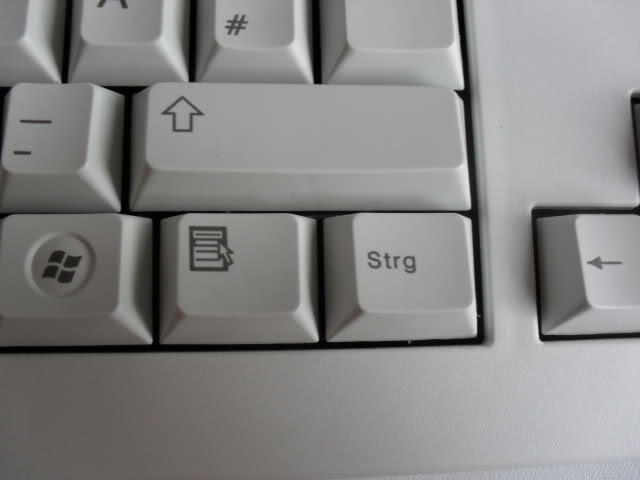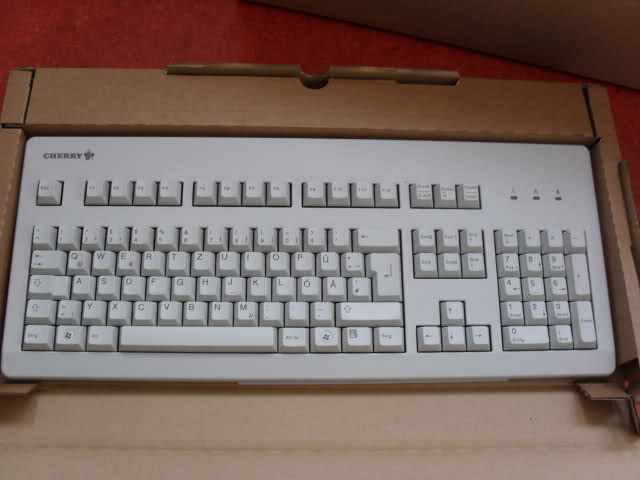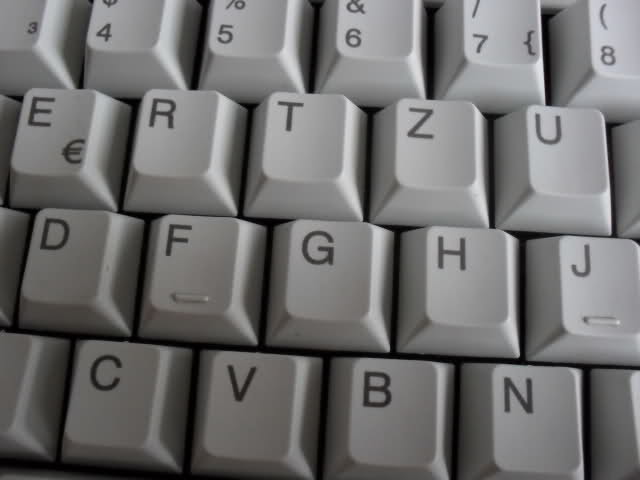
Tastenbeschriftung der Tastatur Cherry G80-3000
Ich will noch mal eine richtige Bestätigung haben, mit welchem Font da meine kürzlich erstandene G80 :) beschriftet ist:
Das müsste doch Helvetica sein, würde ja auch passen, altbewährte Tastatur mit einem guten altbewährten Font :gimmifive:.
Und dann interressiert mich dann auch noch die Schriftart des Cherry-Schriftzugs, damit wenigstens etwas zum Suchen dabei ist ;-).
Falls das Bild zu wenig Details hat, mache ich noch andere.
ich habe mehrere Cherry-Tastaturen (etwas älter als die Tastatur auf der gezeigten Abbildung) und würde für diese behaupten: Die Großbuchstabensehen aus wie Helvetica Rounded mit einem modifizierten großen G. Diesem wurde der senkrechte Balken geklaut. Für die Akronyme auf den Tasten (Alt, Strg ...) hat man ein abweichendes kleine t wie aus den ganz alten Schriftmustern der DIN 1451 Mittelschrift. Das ist vmtl. eine Sonderanfertigung. Aber ich bin nicht sicher ob es da Variationen gab und die neueren Tastaturen wirklich eine echte Helvetica haben. Die Tastaturen von DEC, Compac und PACOM haben alle komplett Helvetica.
ich habe mehrere Cherry-Tastaturen (etwas älter als die Tastatur auf der gezeigten Abbildung) und würde für diese behaupten: Die Großbuchstabensehen aus wie Helvetica Rounded mit einem modifizierten großen G. Diesem wurde der senkrechte Balken geklaut.
Die hier ist ganz neu und das G hat auch einen senkrechten Balken:
Für die Akronyme auf den Tasten (Alt, Strg ...) hat man ein abweichendes kleine t wie aus den ganz alten Schriftmustern der DIN 1451 Mittelschrift.
Meine Steuerungstaste ist so beschriftet:
die gezeigte Tastatur unterscheiden sich bzgl. der Beschriftung von den älteren Cherry-Tastaturen die ich habe. Sie hat eine normale Helvetica (wie auch die Tastaturen vieler anderer Hersteller), die Älteren die von mir beschriebene Schrift. Da gab es wohl früher mindestens eine Extrawurst.
Hier mal einige Fotos von der Schrift die ich auf meinen G81 Tastaturen habe:
Dort findet man oben rechts eine Auswahl mit kleinen Vorschaubildchen. Die beiden Tastaturen mit den orange + gelb + roten Tasten haben die gleiche Schrift wie ich sie auf den normalen G81 sehe. Die Schrift scheint eine sinnvolle Konstruktion für den Druck auf Plastik und ähnliches zu sein. Ich gehe aber davon aus dass es diese Schrift nicht im Handel gibt und der Name, so sie überhaupt einen Namen außer der Bestellnummer hat, weitgehend unbekannt ist.
Ps: Ich war bisher davon überzeugt das Cherry alle Tastaturen mit dieser Schrift ausliefert um sich von der Helvetica-nutzenden Konkurrenz abzugrenzen.
Hier mal einige Fotos von der Schrift die ich auf meinen G81 Tastaturen habe:
Dort findet man oben rechts eine Auswahl mit kleinen Vorschaubildchen. Die beiden Tastaturen mit den orange + gelb + roten Tasten haben die gleiche Schrift wie ich sie auf den normalen G81 sehe.
Ps: Ich war bisher davon überzeugt das Cherry alle Tastaturen mit dieser Schrift ausliefert um sich von der Helvetica-nutzenden Konkurrenz abzugrenzen.
Die Schriftart scheint schon eine ganze Weile Helvetica zu sein, jedoch habe ich kein Bild von Cherry G80 ohne Windows-Tasten bzw. mit Windows-Tasten in der 1. Generation, also nicht im Vista- oder dem vorherigen XP-Stil, bei dem die Taste noch normal geformt war, und das Windows-XP-Logo oben links stand. Irgendwie finde ich diesen Kreis um das Windows-Symbol (der wahrscheinlich von Microsoft aufgezwungen wurde) übertrieben, oder soll man jetzt diese Taste leichter finden?
Hier mal einige Fotos von der Schrift die ich auf meinen G81 Tastaturen habe:
Dort findet man oben rechts eine Auswahl mit kleinen Vorschaubildchen. Die beiden Tastaturen mit den orange + gelb + roten Tasten haben die gleiche Schrift wie ich sie auf den normalen G81 sehe.
Eine G81, das ist doch nur eine Zwischenlösung. Wenn dann das richtige nehmen und eine G80 kaufen und wenn die leiser sein muss, dann eben mit Soft-Druckpunkt.
Kaufen? Die Cherry G81 habe ich in größeren Stückzahlen geschenkt bekommen und sie sind gut genug dass sich ein Neukauf definitiv nicht rechnen würde. Daher benutze ich diese noch bis zum natürlichen und technischen Ableben. Ansonsten habe ich noch eine alte DEC-Tastatur die der Cherry G80 qualitativ nahe steht und zwei alte NONAMES (made in China, mit Compac und Commodore gelabelt) die ebenfalls recht gut sind. IMHO sind diese um einiges robuster und zuverlässiger als die G81. Adapter DIN auf PS/2 und diese Tastaturen können verwendet werden.
Nein, die Umstellung muss schon zu Windows XP passiert sein, da ist die Beschriftung gleich wie bei Vista, nur die Windowstaste hat das Logo in der linken oberen Ecke und die Taste ist normal geformt.
Und die Frage nach Logo-Schrift ist ja auch noch offen.